Buat font IG keren dan unik untuk bio dan caption IG dengan tool Instagram Font Generator
Gaya font default Instagram yang cenderung membosankan membuat sebagian pengguna ingin menggantinya dengan gaya font yang lebih keren dan unik. Untuk mengubah teks normal menjadi teks yang keren dan unik, Anda dapat menggunakan tool IG font generator yang kami buat secara gratis untuk para pengguna Instagram. Instagram font generator adalah tool online yang dapat Anda gunakan untuk mengubah teks normal menjadi teks dengan gaya fancy dan aesthetic.
Dengan tool Instagram font generator, Anda dapat mengubah teks normal yang Anda ketikan ke beragam gaya font yang unik, keren, dan elegan. Pilihannya gaya font cukup banyak, mulai dari font tebal, font miring, font latin, font simbol, font Jepang, font Thailand, font Korea, font Arab, vaporwave, karakter unicode, karakter ASCII, emoji, dan beragam jenis gaya font lainnya. Jika Anda suka dengan gaya font yang dihasilkan, Anda bisa pilih salin dan tempelkan ke profil akun Instagram Anda.
Instagram font generator bekerja secara otomatis dan real-time saat Anda mengetikan teks di kolom yang tersedia. Jadi, silakan ketikan atau tempelkan (paste) teks yang Anda inginkan ke kolom yang tersedia di bawah ini. Selanjutnya, algoritma dari tool ini akan menghasilkan beragam gaya font secara real-time untuk Anda. Untuk menyalin teks, Anda bisa klik tombol “Copy” yang ada di sebelahnya, lalu Anda bisa tempelkan ke bio Instagram Anda. Untuk melihat gaya font teks lain, Anda bisa klik “Load more” yang ada di bagian paling bawah dari kolom font cute typing.
Setelah membuat dan menyalin teks keren yang Anda buat dari tool di atas, sekarang Anda bisa menambahkannya di profil Instagram Anda. Berikut panduan singkat menambahkan teks keren di bio dan caption Instagram yang dapat Anda simak dan ikuti!
Pertama, Anda bisa menambahkan teks keren di profil bio Instagram Anda. Simak dan ikuti cara mudah menambahkan bio Instagram di bawah ini.
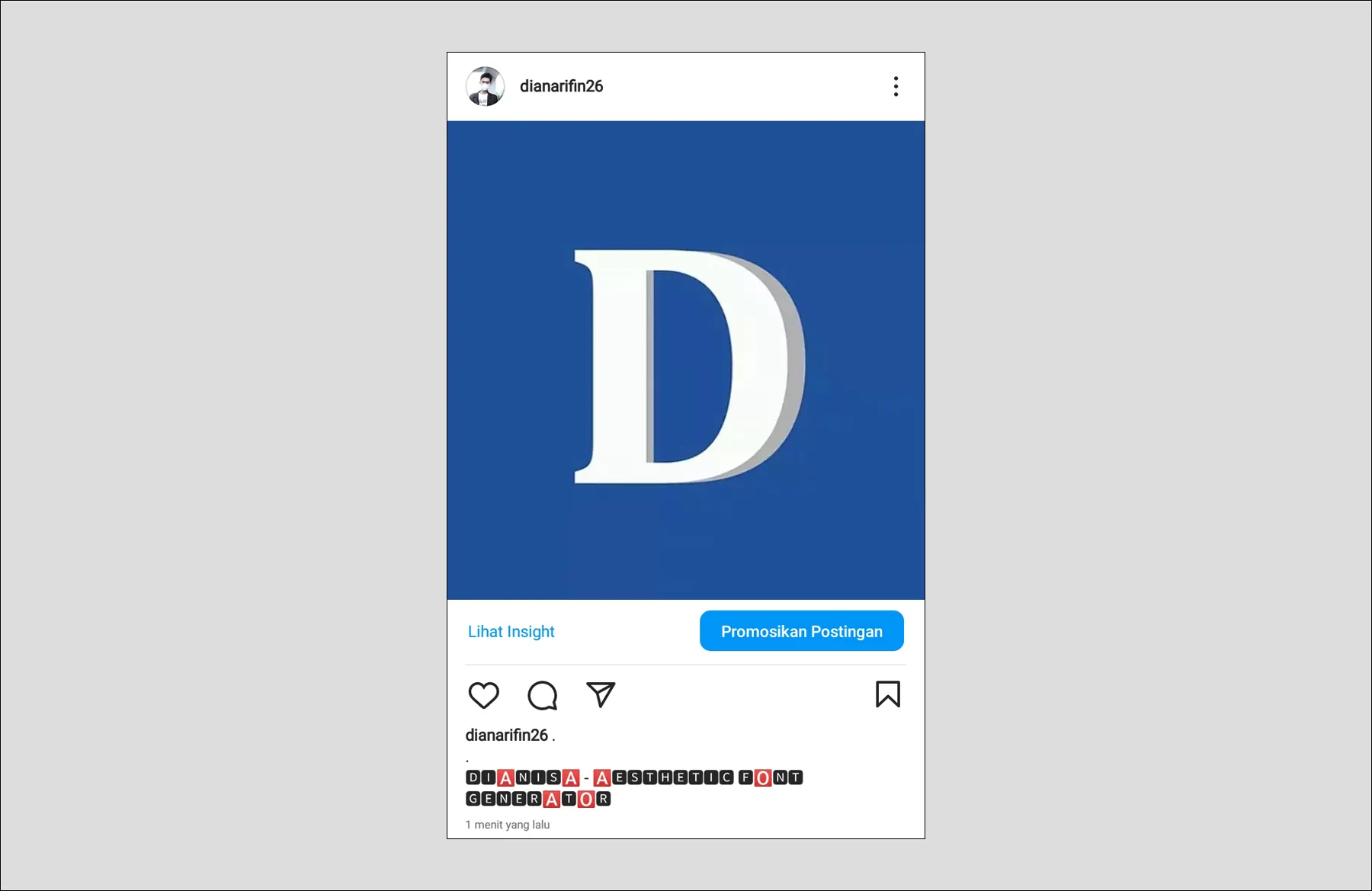
Selain bio, Anda juga bisa menambahkan teks keren ke caption foto atau video yang Anda upload. Caranya sangat mudah, simak dan ikuti langkah-langkahnya di bawah ini.
Instagram font generator memungkinkan Anda dapat mengubah teks normal menjadi teks keren dan aesthetic. Dibalik dari tool ini, ada algoritma canggih yang bekerja secara otomatis dan real-time untuk menghasilkan font teks yang unik dan keren. Hasilnya, ada lebih dari 80 font teks yang bisa Anda salin dan tempelkan ke profil Instagram Anda. Tidak hanya untuk bio Instagram, Anda bisa memanfaatkan tool ini untuk membuat pesan WhatsApp, bio TikTok, Facebook, Twitter, dan lain-lain. Anda bisa menggunakan tool ini di browser PC, laptop, atau HP Anda.
Tentu saja bisa. Tool ini dapat Anda akses pada perangkat apa pun yang memiliki browser, seperti Google Chrome, Microsoft Edge, Mozilla Firefox, Opera, dll, baik itu PC, laptop, maupun smartphone. Jadi, Anda bisa menggunakan tool ini melalui browser Safari di iPhone (iOS) Anda.
Silakan ketik atau paste teks yang Anda ingin generate ke font keren ke kolom yang tersedia. Kemudian teks yang Anda masukkan tersebut secara otomatis dan real-time akan di generate ke beragam font keren dan unik. Selanjutnya, Anda bisa memilih dan menyalin font teks dengan klik ikon “Copy” yang ada di sebelahnya, lalu menempelkannya (paste) ke profil Instagram yang Anda miliki. Klik tanda centang untuk menyimpan perubahan.